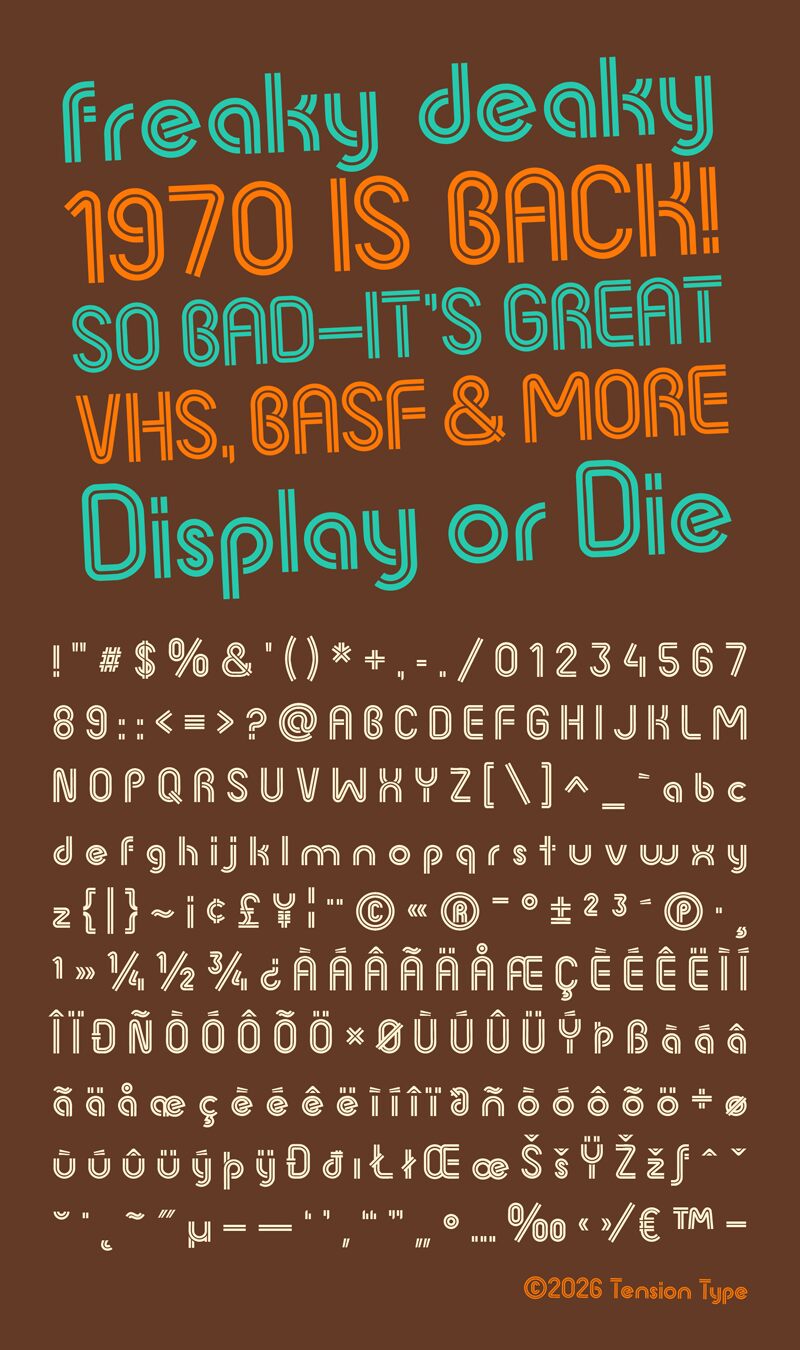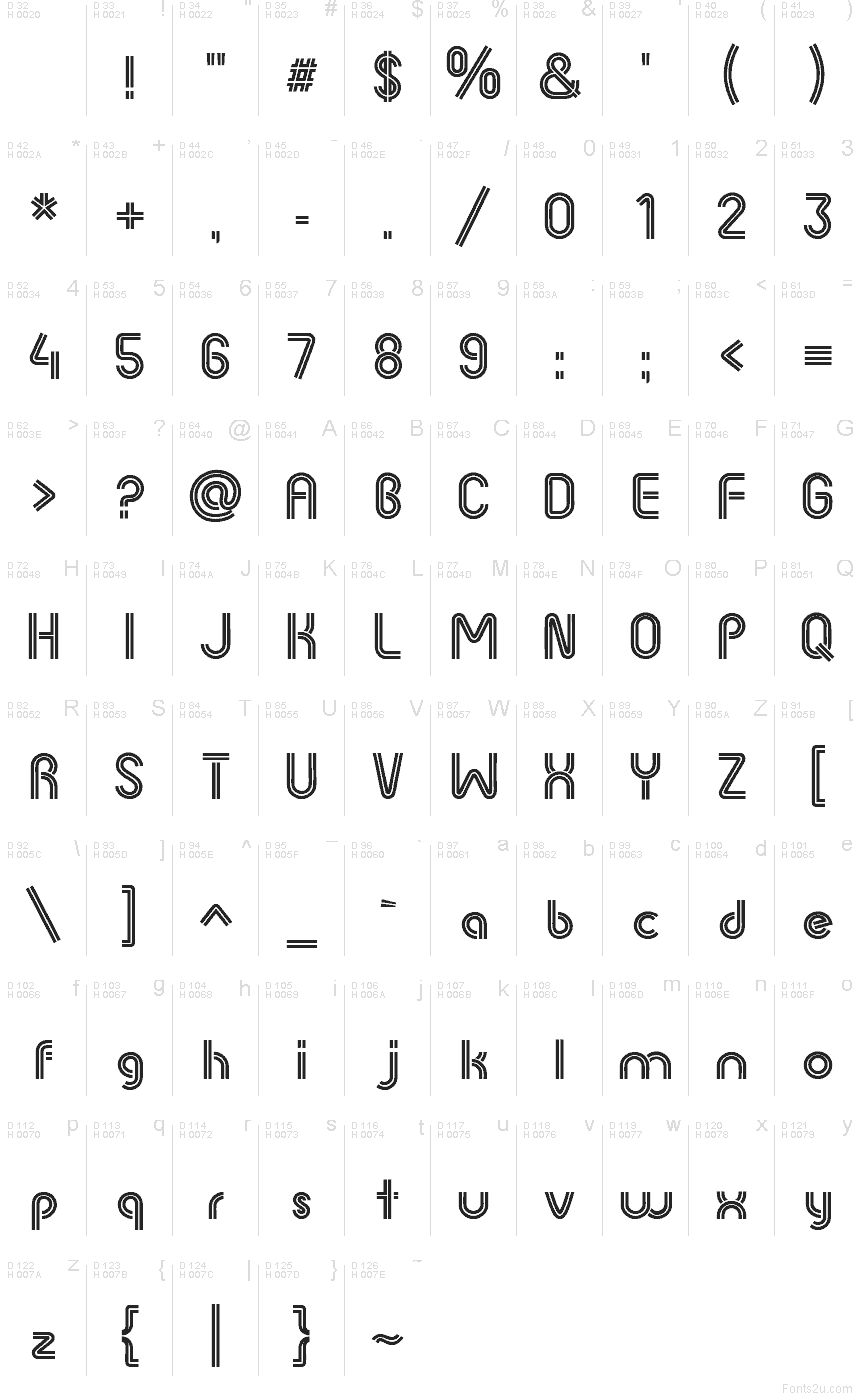
1970 Porno Regular
1970 Porno de Tension Type es una fuente display gratuita de estilo groovy, con contornos redondeados y una doble línea que recorre cada forma. Los caracteres son altos, suaves y muy curvos, lo que le da a la familia un ritmo propio de la cartelería de los años 70 sin añadir adornos extra.
1970 Porno funciona muy bien en portadas de álbumes, flyers de eventos retro, logotipos, señalética y titulares que busquen ese toque gráfico sellado y propio de la época. Esta fuente gratuita cuenta con la estructura suficiente para sostenerse en cuerpos grandes, mientras que su construcción calada la hace muy práctica para packaging, tarjetas de título y una identidad visual decorativa y atrevida.
Este diseño comenzó como tipografía personalizada para un logo; al principio solo se crearon unas pocas letras. Lo expandí hasta convertirlo en un alfabeto completo y desarrollé la familia tipográfica. Esta fuente está destinada únicamente a uso en pantallas y titulares.
This design started as custom type for a logo design. There were only a handful of letters created. I took the time to make the entire alphabet. Then, though this font is only good for display, made a full typeface. It’s very retro.